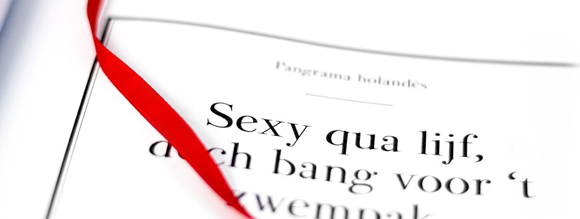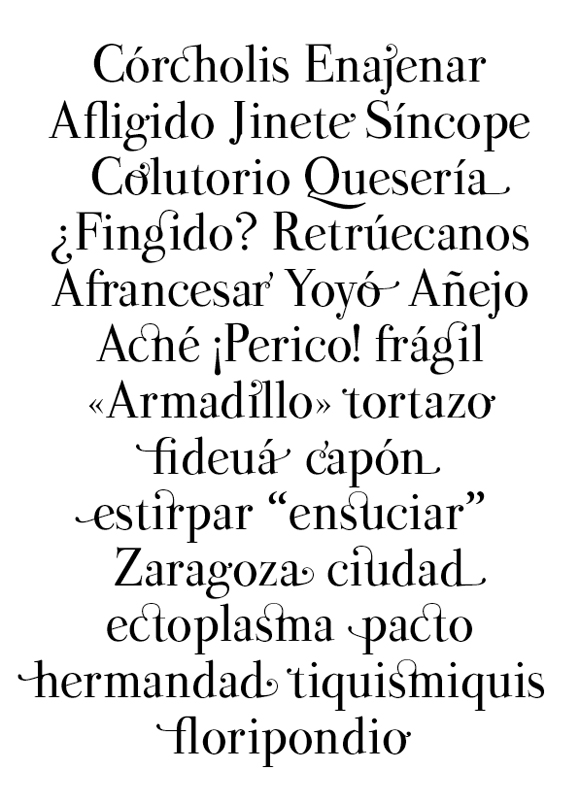
El diseñador gráfico Pedro Arilla ha presentado en sociedad a su última creación tipográfica: Valentina. En sus propias palabras: «La tipografía Valentina es un sincero homenaje a mi abuela en forma de tipografía y por ello lleva su nombre. Valentina es una didona clásica que sigue algunos de los cánones propuestos por Bodoni en el siglo XVIII pero incorporándole muchos de los rasgos característicos de los punzones castellanos de la época. Es una tipografía completa que consta de 457 glifos, entre los que destacan los 125 caracteres latinos alternativos en caja baja o las 46 ligaduras.»
A nosotros nos parece una apuesta interesante que indaga en la historia de la tipografía española incorporando en su diseño, por ejemplo, las pequeñas proyecciones en la j conocidas por «gilismos» y popularizadas por Gerónimo Gil en el siglo XVIII, una evidente modulación vertical y un contraste abrupto en sus trazos propios de los diseños bodonianos así como ciertos anacronismos como el perfil oblicuo de la e que dotan al conjunto de un encanto especial. Se acompaña con una variedad destacable de ligaduras tanto clásicas como de fantasía y letras rasgueadas que hacen de Valentina una tipografía muy apta para trabajos exquisitos en los que las formas tipográficas sean llamadas a tener un protagonismo visual claro.